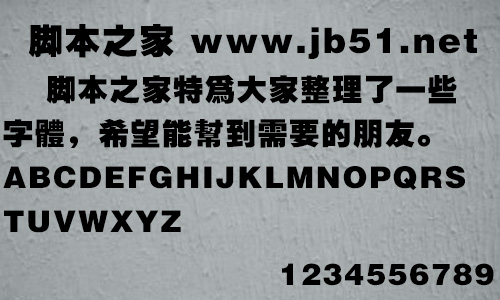
方正超粗黑繁體字體是方正字體庫(kù)中的一種繁體字體,該字體筆觸較為粗實(shí),具有很好的視覺(jué)感染力,適合應(yīng)用于藝術(shù)設(shè)計(jì)、平面宣傳設(shè)計(jì)、網(wǎng)頁(yè)設(shè)計(jì),書(shū)法字帖等領(lǐng)域,喜歡的朋友們可以前來(lái)下載使用。